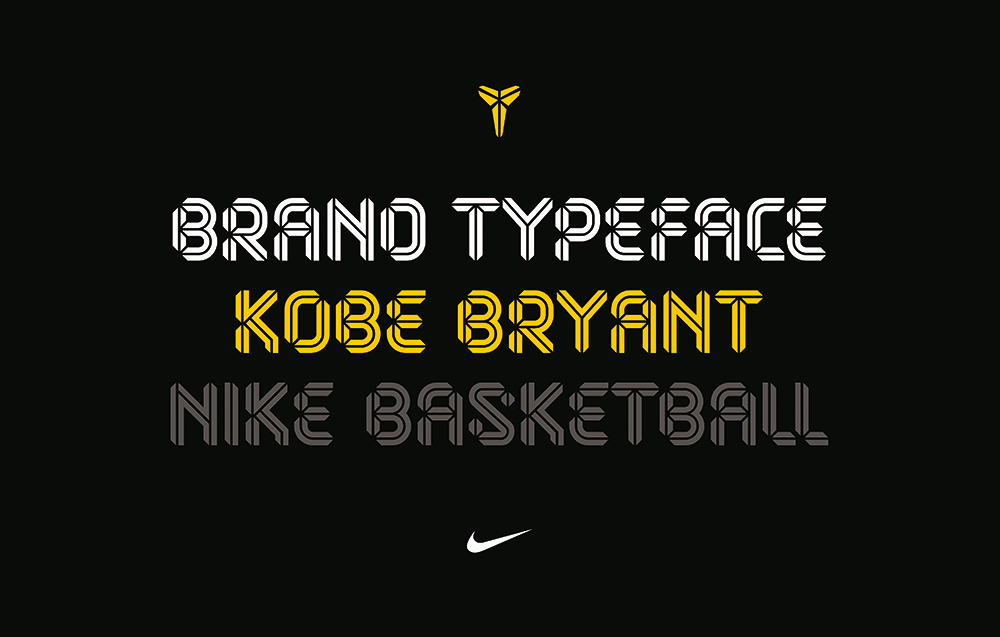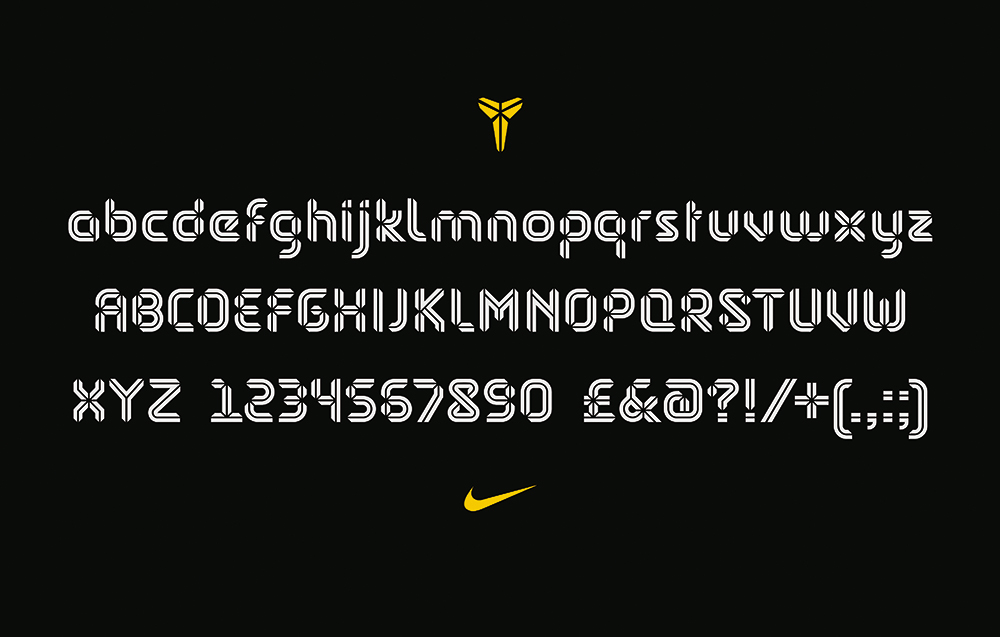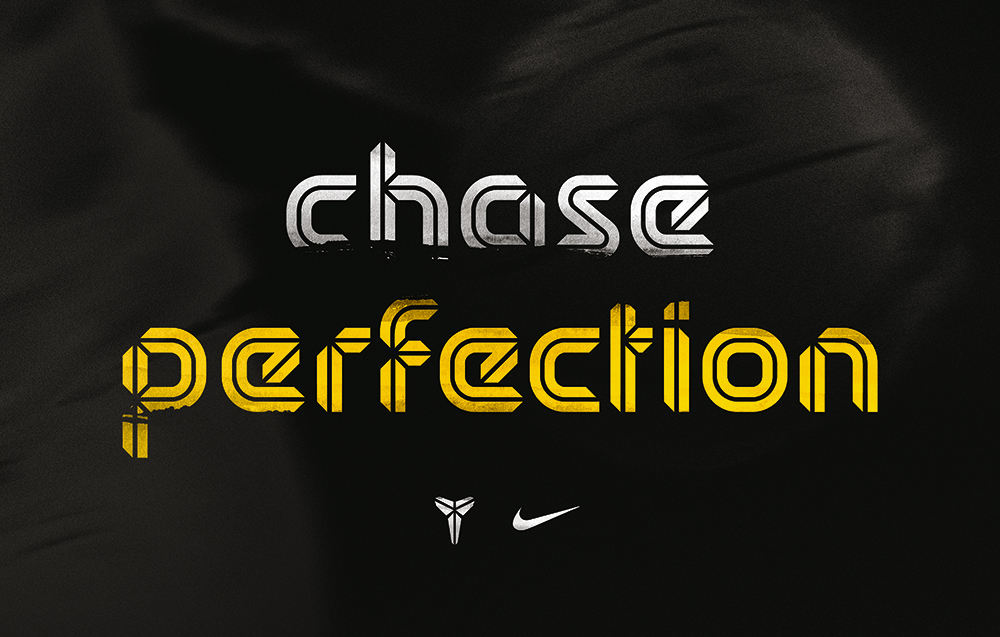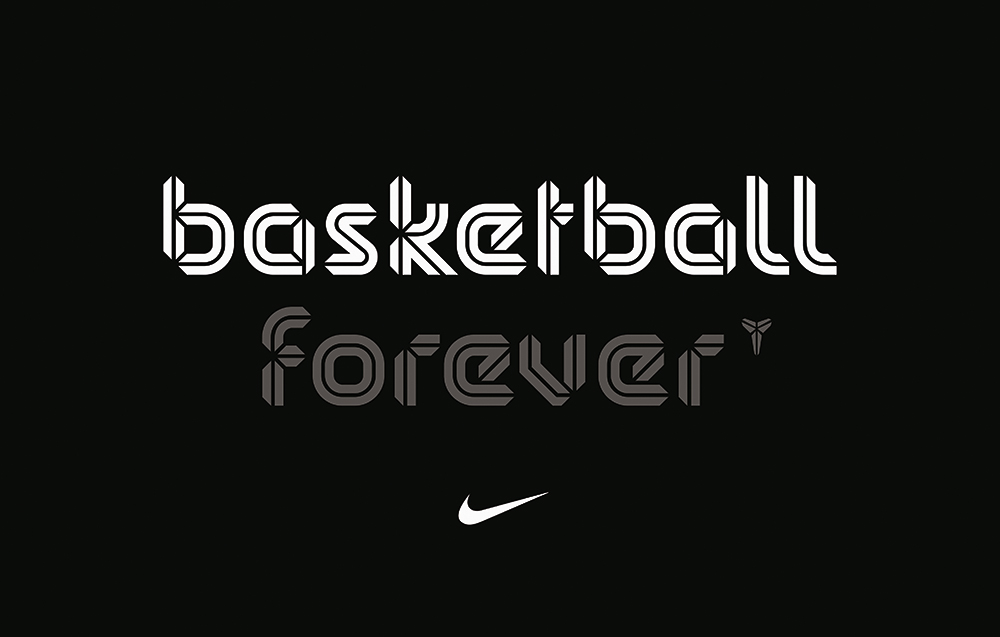
코비 브라이언트 브랜드 서체 : 농구여 영원하라!
런던의 크리에이티브 에이전시 소더스트는 나이키의 의뢰로 농구선수 코비 브라이언트를 위한 완전히 기능적인 디스플레이 서체를 개발하게 되었다. 브라이언트의 기존 로고 ‘sheath’를 이용해 맞춤형 무언가를 만들어 내는 것이 구체적인 의뢰 내용이었는데 이 로고는 기존 브랜딩과 궤를 함께 하며 확장될 필요가 있었다.
코비 브라이언트(Kobe Bryant) 브랜드 서체 : 농구여 영원하라!
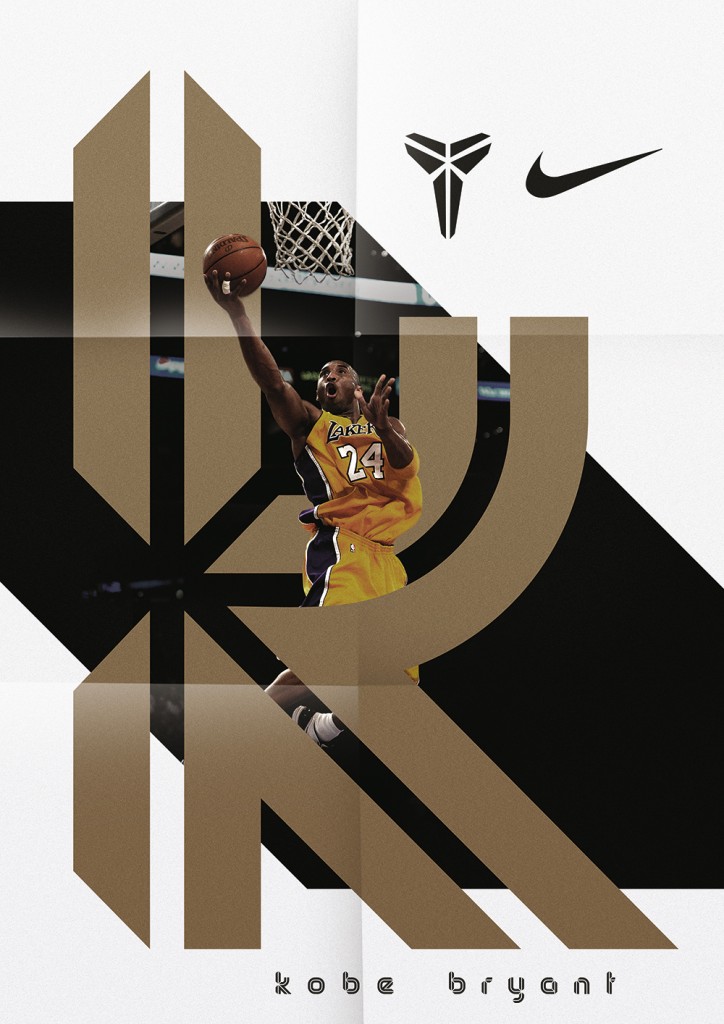
“여느 맞춤형 서체처럼 우리의 발상은 이 브랜드를 위해서 단독으로 존재하는 무언가를 만드는 것이었죠. 우리는 나이키 디자이너들과 긴밀히 협력해서 독자적이고 다재다능하며 브랜드와 깊게 연관된 무언가를 구현하고자 했습니다. 이는 시선을 잡아끌고 당당하면서 튀는 무언가를 디자인해야 한다는 점을 의미했습니다. 마치 코비 자신처럼요.”
소더스트의 공동설립자 롭 곤잘레스(ROB GONZALEZ)가 설명한다.
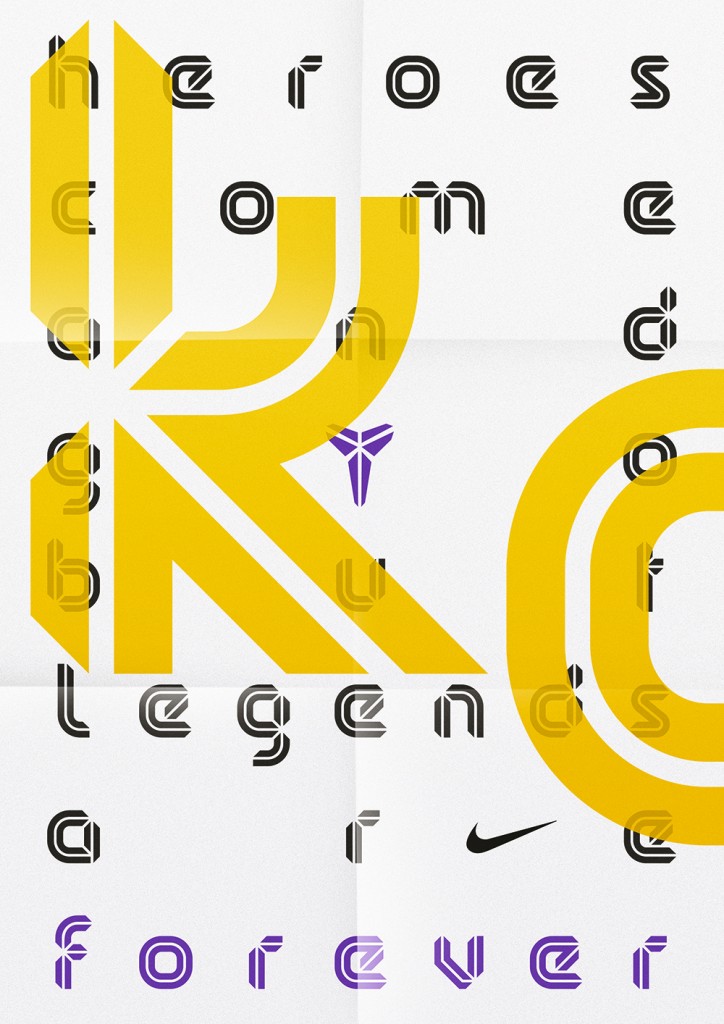
주된 과제는 기존 로고를 보완하면서 독특한 서체를 만들어 내는 것이었다. “우리는 음화적 공간과 로고 마크의 중심점으로부터 영감을 얻었습니다. 이 요소들은 글자꼴의 기반 구조를 형성하게 되었죠.” 곤잘레스가 덧붙인다.